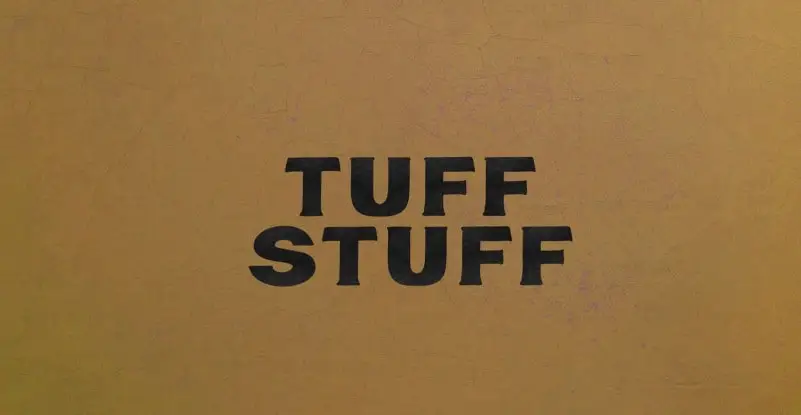
Tuff Stuff Serif Font – Download Grátis
Tuff Stuff Serif é uma fonte serif que emociona através de sua inspiração no mundo ao ar livre. Feita com amor e alegria, essa elegante tipografia foi criada pela blkbktyp para dar um toque único aos seus projetos digitais. Inspirada em tudo entre o espetacular céu da natureza na floresta até as águas calmas do mar, essa multilingue fonte traz uma atmosfera nostálgica de velha escola de vida selvagem para seu projeto. Com Tuff Stuff Serif você pode deixar que a sua arte fale por si mesma e seja notada em um mundo cada vez mais digital. Adquira-a hoje para levar um pedacinho da natureza para seu próximo projeto.